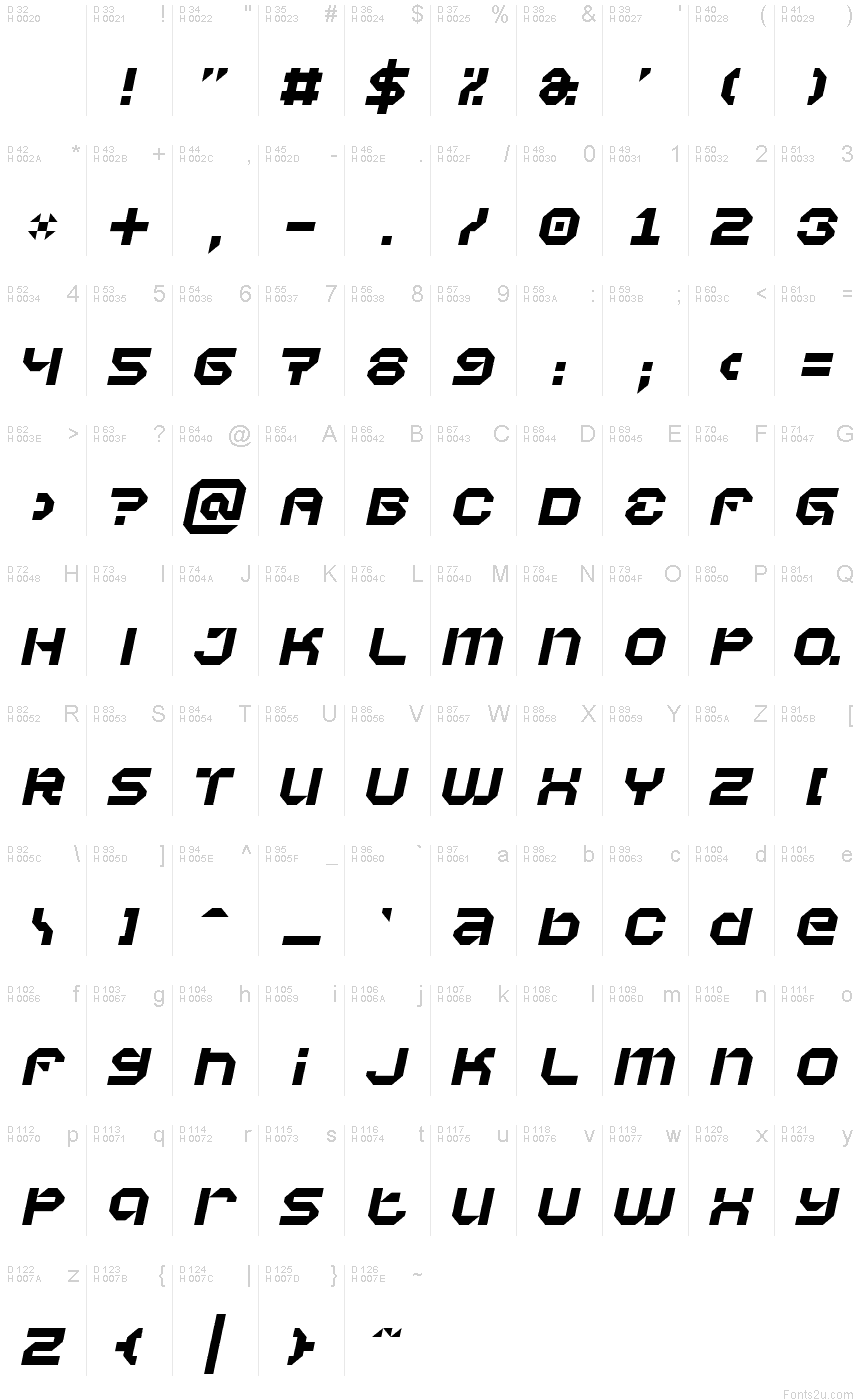
Vaporbyte Italic
Vaporbyte Italic, bezplatné, hranaté techno písmo typu display od dustBUST Fonts, sází na rychlost rané digitální éry: má řezané diagonály, špičaté spoje a dravý sklon vpřed. Písmena působí strojově, ale ne chladně; masivní tvary s ostrými klíny dodávají celému písmu dravý herní charakter.
Skvěle zapadne do sci-fi plakátů, arkádové grafiky, obalů alb, náhledů pro streamy nebo titulků, kde pár slov potřebuje ten správný elektronický švih. Jelikož jde o bezplatné písmo, výborně se hodí i na krátká loga, hlavičky rozhraní nebo nadpisy, zejména pokud chcete, aby text působil dynamicky i bez použití zjevných efektů.